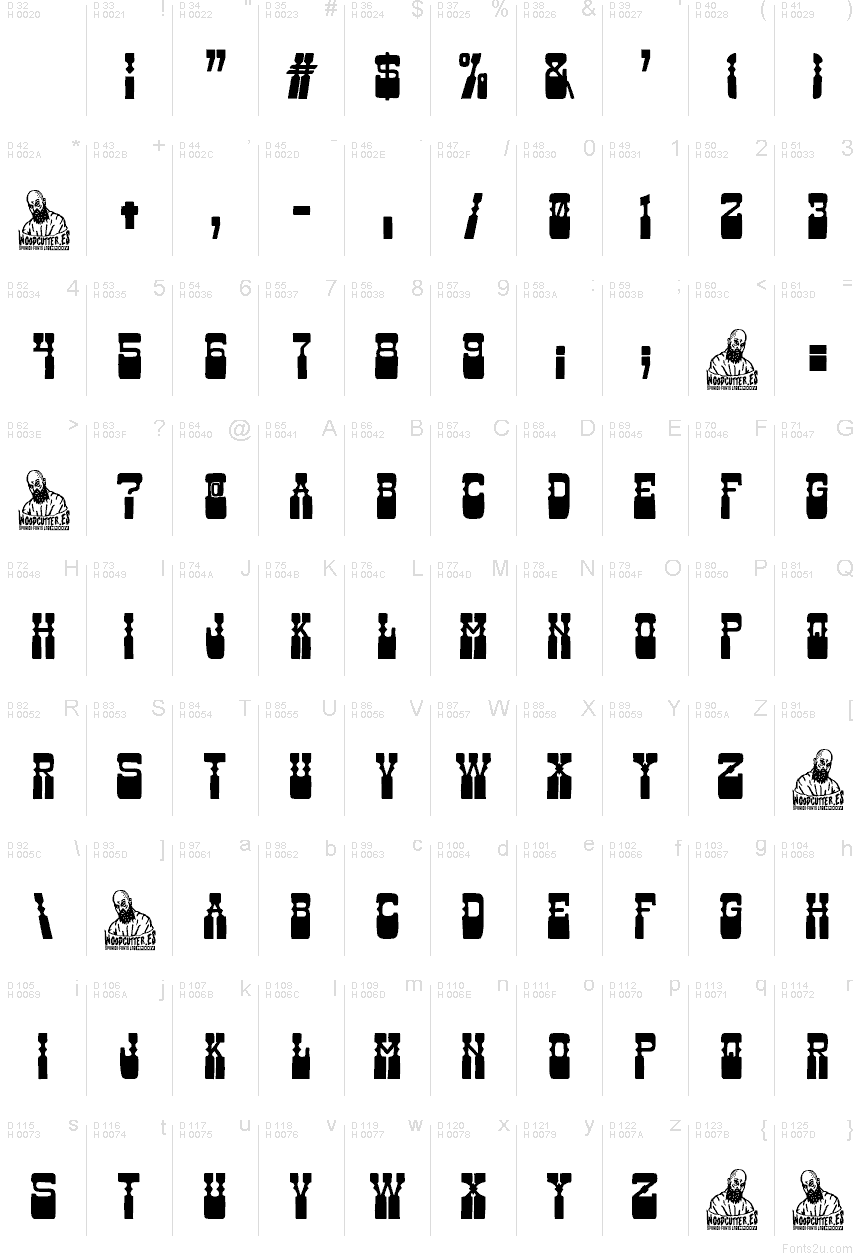
Super Cowboy od Woodcutter Manero je bezplatné westernové displejové písmo s atmosférou starých saloonů. Písmena jsou masivní, těsně u sebe, s výraznými blokovými tvary, hranatými křivkami a charakteristickými zářezy, které dodávají znakům surový, téměř do dřeva vytesaný vzhled, zcela odlišný od uhlazených moderních stylů.
Hodí se pro tvorbu plakátů, branding rodeí a country festivalů, etikety na whisky, vintage výlohy obchodů i výrazné nadpisy, kde krátký titulek potřebuje ten správný westernový říz. Jakožto bezplatné písmo skvěle poslouží i pro titulní karty, skici log a monogramy, protože jednotlivé znaky mají dostatek hmoty a charakteru, aby obstály i samostatně.